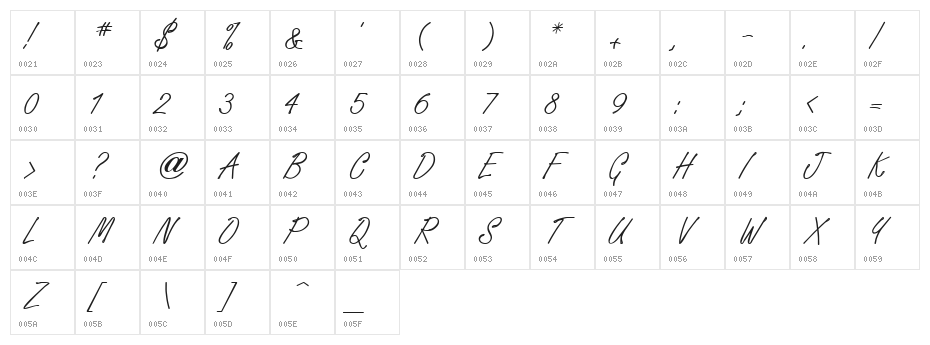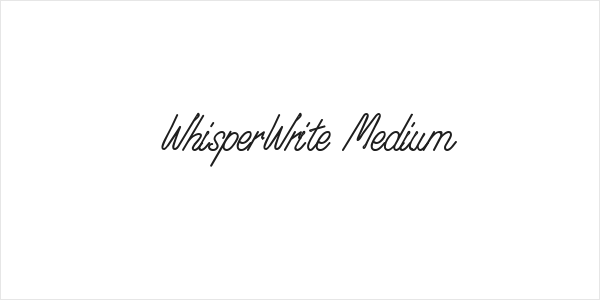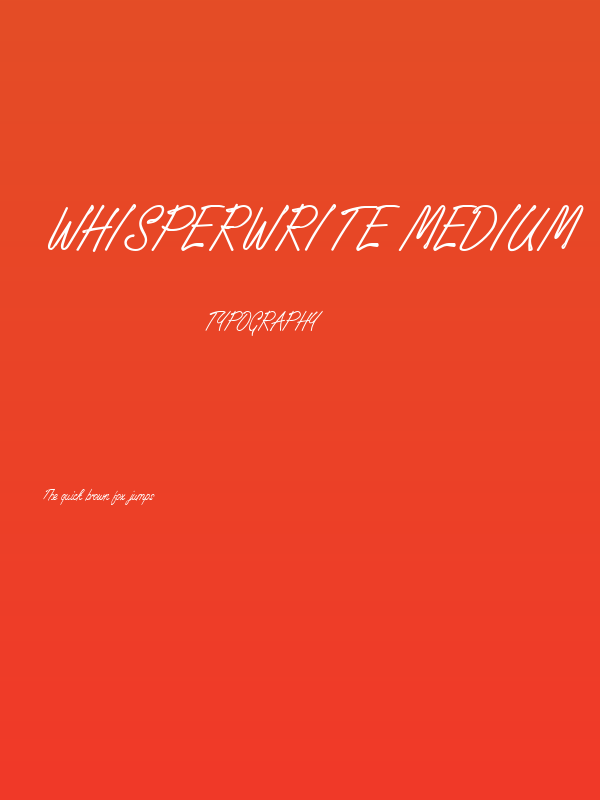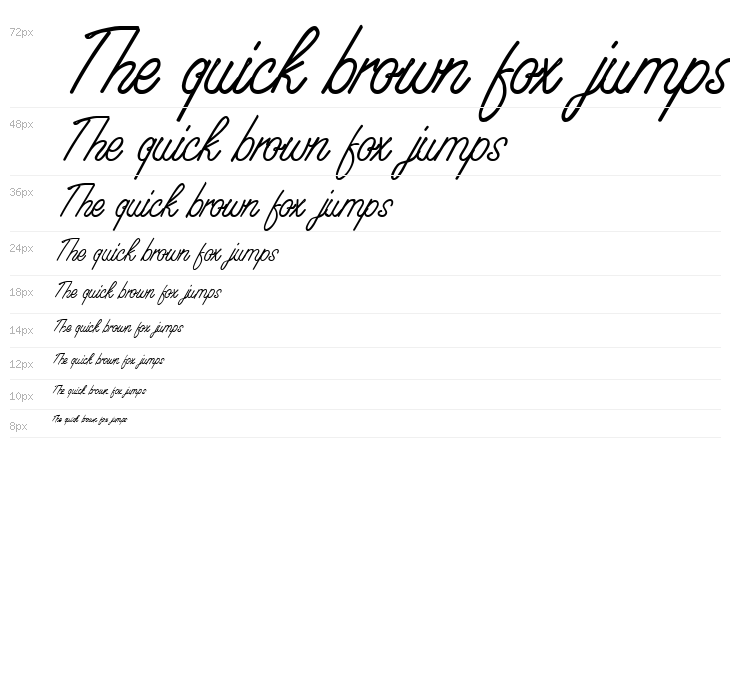
WhisperWrite Medium Font
Diese Schriftart enthält 171 Zeichen. Klicken Sie auf ein Zeichen für Details.
WHISPERWRITE-MEDIUM Groß
WHISPERWRITE-MEDIUM Kleinbuchstaben
WHISPERWRITE-MEDIUM Anderer Schreiben
| Gesamtstil | Elegant, Handwritten |
| Anwendungsfall | Logos, Invitations, Artistic projects |
| Vorgeschlagene Projekte | Ideal for wedding invitations, personal branding, greeting cards, and artistic projects. |